5 font ad alta leggibilità per i tuoi progetti grafici
Cosa succede quando un potenziale cliente non riesce a leggere facilmente un’etichetta? Probabilmente, non potendo ottenere le informazioni necessarie per compiere la scelta, passerà ad un altro prodotto. Un testo difficilmente leggibile non è solo sgradevole dal punto di vista visivo ma potrebbe davvero fare la differenza – negativamente – in termini di vendita. Ecco dunque una lista di cinque font ad alta leggibilità su cui puntare ogni volta che volete essere certi che il messaggio arrivi chiaramente al destinatario.
Quando si devono inserire molte informazioni in uno spazio relativamente ristretto come quello di un’ etichetta adesiva bisogna assicurarsi che ogni parte del testo sia perfettamente leggibile. Per garantire questo risultato è necessario adottare una serie di accortezze: prediligere colori scuri su uno sfondo chiaro, scegliere carte patinate e, ovviamente, assicurarsi di utilizzare un font ad alta leggibilità.
1. Helvetica
Come abbiamo visto in precedenza, Helvetica (inserire link: https://www.labelado.com/it/blog/font-color/helvetica-font/) è uno dei font migliori da utilizzare quando si è alla ricerca di semplicità e chiarezza. Nato in Svizzera alla fine degli anni ’50, questo font è caratterizzato dalla presenza di uno spazio negativo intorno alle lettere uguale a quello delle linee che circondano i caratteri. Questo fa sì che il testo risulti chiaro e scorrevole anche quando la dimensione del font è ridotta.
2. Futura
Il Futura è un carattere sans serif, geometrico, armonioso e lineare. Nato a metà degli anni ’20 in Germania e fortemente influenzato dalle teorie estetiche del Bauhaus, il font Futura è ritenuto il primo tra i font serif geometrici: ogni lettera si basa in fatti sulle tre forme più elementari, ovvero il triangolo, il quadrato e il cerchio. Questa caratteristica lo rende perfetto per essere utilizzato in tutti i casi in cui è necessario garantire massima leggibilità, sia a dimensioni molto grandi (non a caso è il font utilizzato da Ferrovie Italiane), che molto piccole.
3. Gill Sans
Gill Sans è un font sans serif che pur conservando la geometria elementare della tipografia modernista, mantiene la vivacità tipica della scrittura a mano, ispirato alle lettere classiche romane. Queste caratteristiche gli valsero la definizione di “umanistico”, termine che da quel momento indica tutti i font con queste peculiarità. Questo font ad alta leggibilità dall’aspetto fiero e decoroso è stato utilizzato per moltissimi marchi famosi ed è tutt’oggi uno dei più apprezzati.
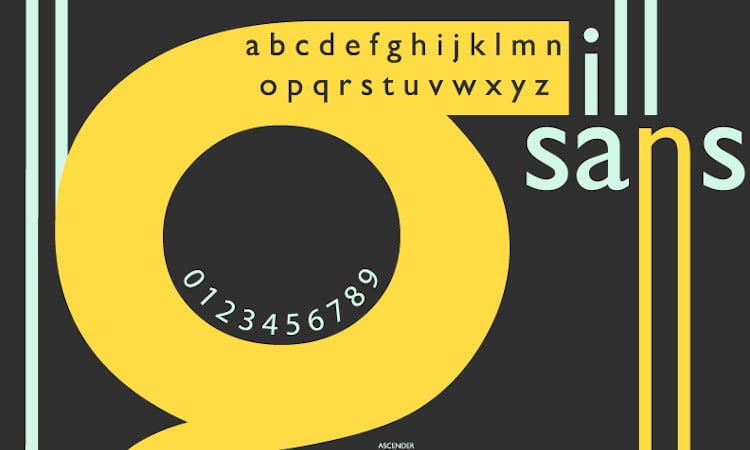
4. Frutiger
Il font Frutiger porta il nome del designer che lo ha creato nel 1968 per il sistema di segnaletica dell’aeroporto Charles De Gaulle a Parigi. Il suo obiettivo era creare un font sans serif che avesse la stessa razionalità e pulizia di Univers ma con la compattezza e l’immediata riconoscibilità di Gill Sans. Il risultato è un font nitido, pulito e riconoscibile, motivo per cui da oltre cinquant’anni è uno dei caratteri più utilizzati nel mondo dell’advertising e della stampa.
5. Arial
Arial è un carattere tipografico reso famoso da Microsoft ma inventato per le stampanti IBM all’inizio degli anni ’80. Sebbene sia spesso ritenuto una variante dell’Helvetica, i suoi designer si ispirarono al font Grotesque. Rispetto a questo presenta tuttavia alcune varianti create appositamente per renderlo un font ad alta leggibilità su schermo.